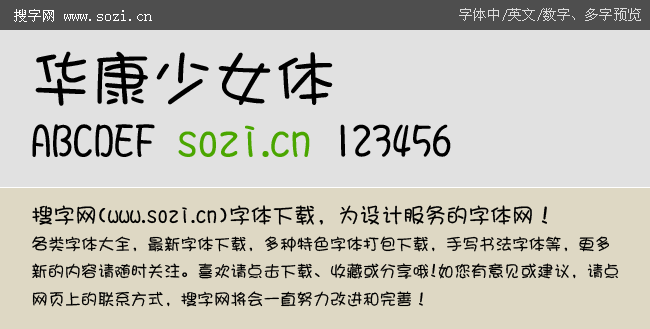
華康少女繁簡完全版
搜字網(wǎng)給大家提供一款華康少女繁簡完全版卡通中文字體下載。華康少女字體電腦版是一款可愛俏皮的電腦字體。字型中充滿年青人蓬勃的氣息與自由奔放的性格,字體相對(duì)其他字體比較圓滑,適合海報(bào)設(shè)計(jì)、包裝設(shè)計(jì)、廣告畫冊(cè)的應(yīng)用。